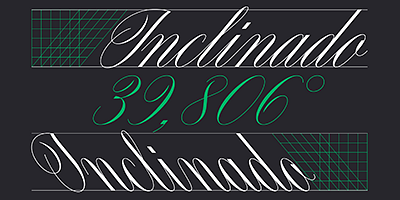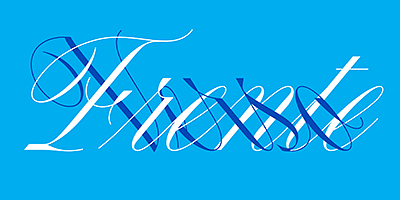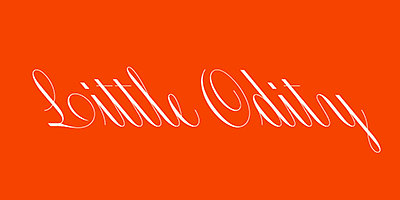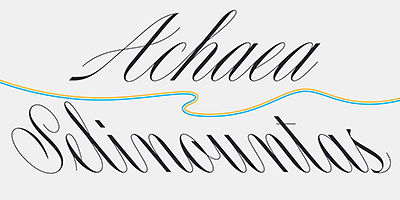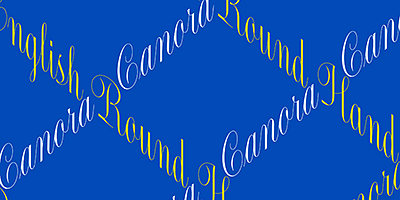
Canora Frente は、流麗で優雅でありながら、構造が驚くほど堅牢な、丸みのある英語の筆記体を力強く解釈した書体です。そのデザインは、直線、急激なカット、様式化されたループとドットを使用して、筆記体のモデルを現代的で機械的な外観にすることを目指しています。一方、Canora Verso は、まれな左傾斜角度で、丸みのある英語の書体が任意のデザイン決定に耐えられることをさらに証明しています。
Canora の 2 つのフォントは、シンプルで幅狭の小文字を特徴としていますが、スワッシュと十分なカーブを備えた適度に豊富なマジャスキュールは、自然に装飾性を高めています。